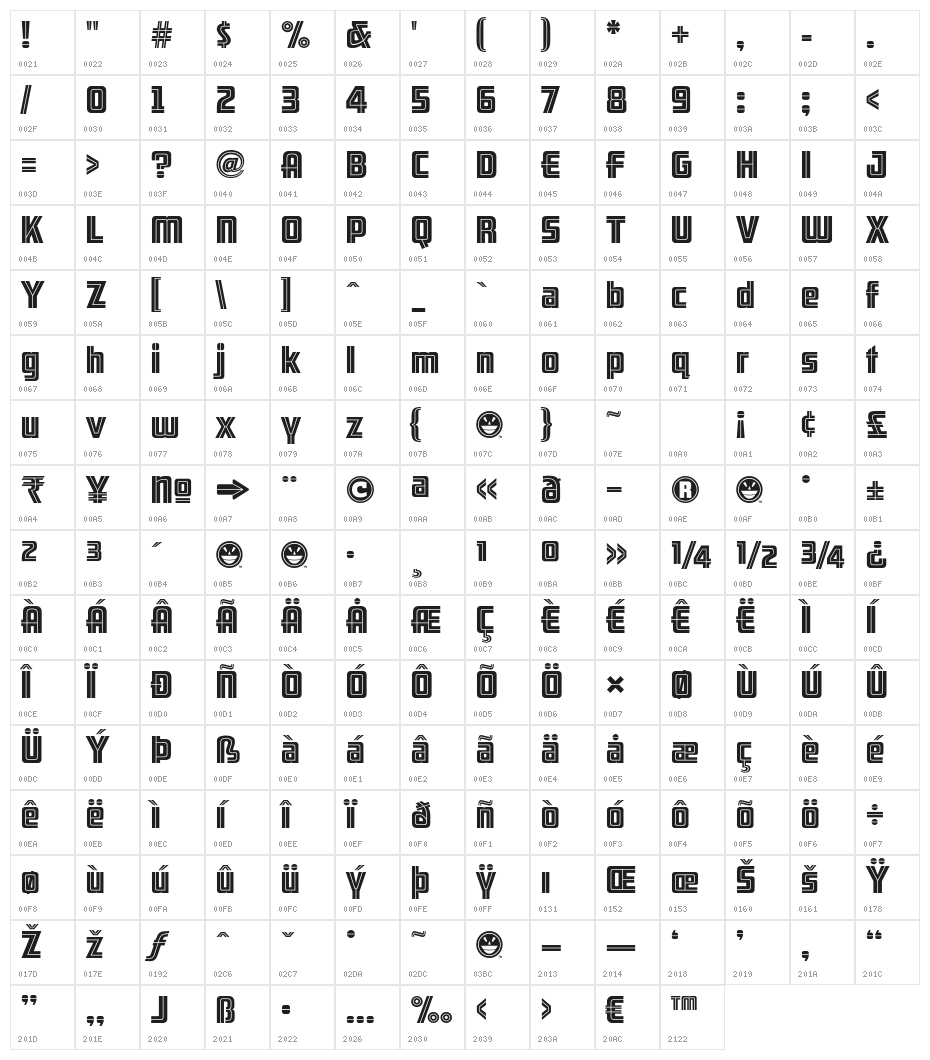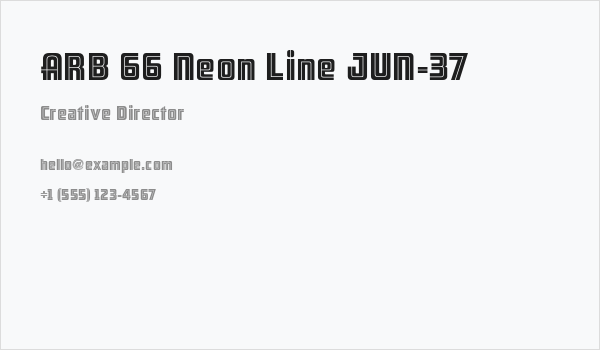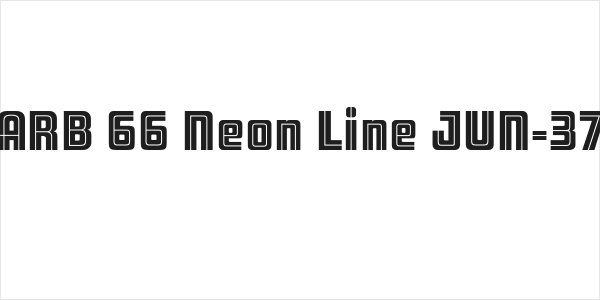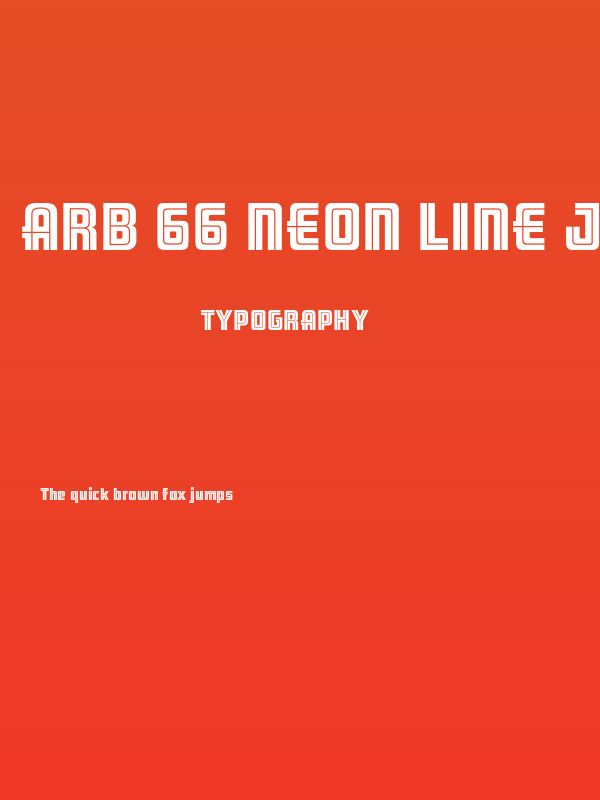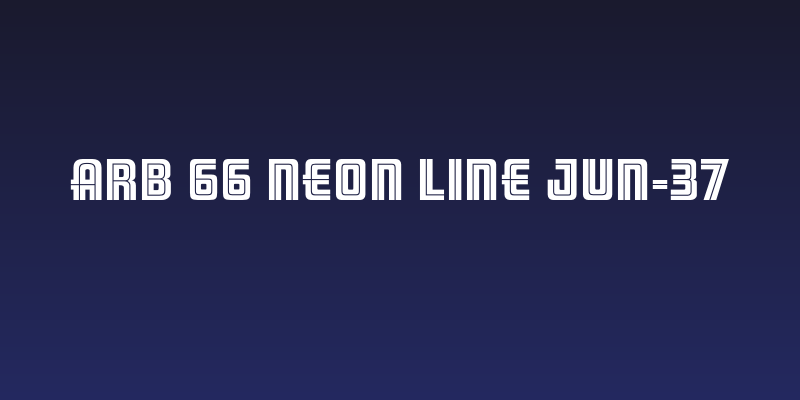
ARB 66 Neon Line JUN-37 Font
✎ Outline
| Progetti proposti | Ideal for projects requiring a futuristic or tech-inspired look, such as digital interfaces, video game graphics, or sci-fi themed posters. |